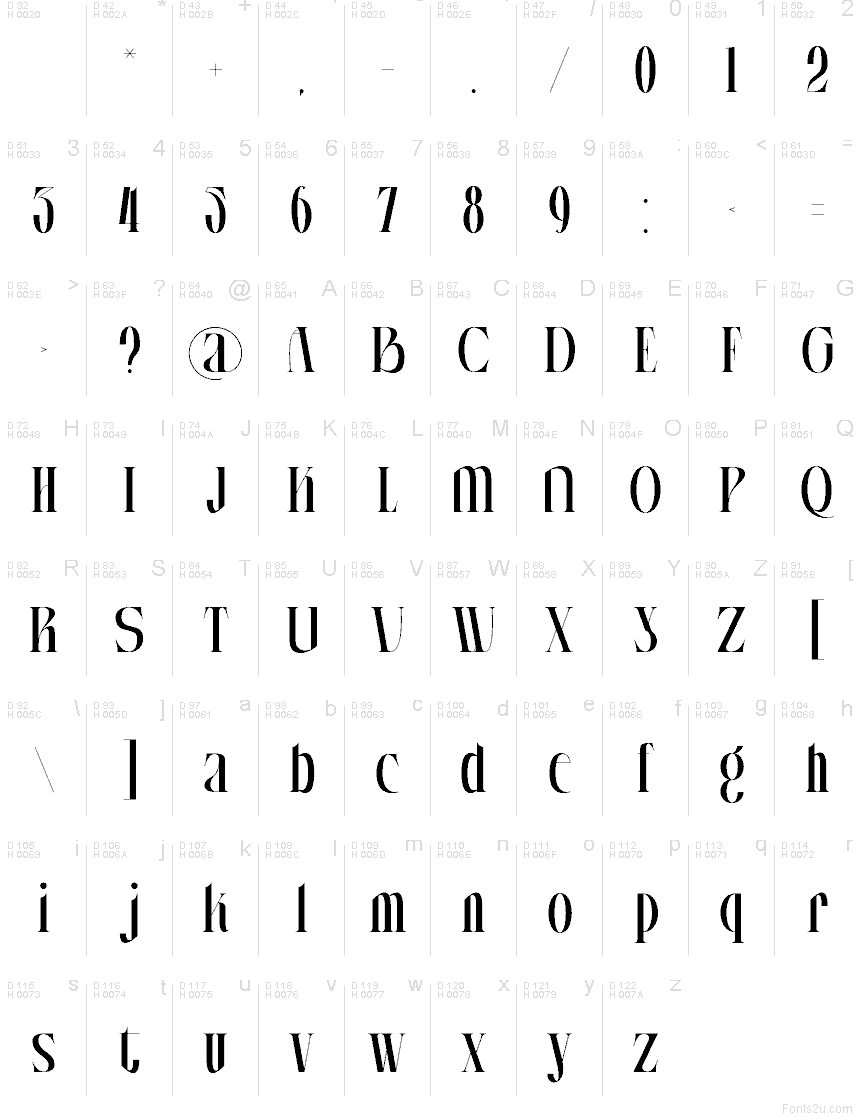
Almanac Zitole Regular
Almanac Zitole, criada pelo Afkari Studio, é uma fonte serifada vintage gratuita com um toque teatral típico da era dos cartazes clássicos. As suas letras combinam curvas espessas e aveludadas com traços finos e cortes precisos, conferindo à fonte um estilo editorial dos anos 60 e 70 que é, ao mesmo tempo, elegante e levemente psicadélico.
Encaixa-se naturalmente em cabeçalhos de revistas, capas de álbuns, embalagens de boutiques, branding de cafés e títulos de filmes, onde o seu ritmo de alto contraste é capaz de destacar uma frase curta por si só. Sendo uma fonte gratuita, também faz sentido para títulos de capa, monogramas e outros usos decorativos curtos que precisem de algo elegante, mas bem composto.